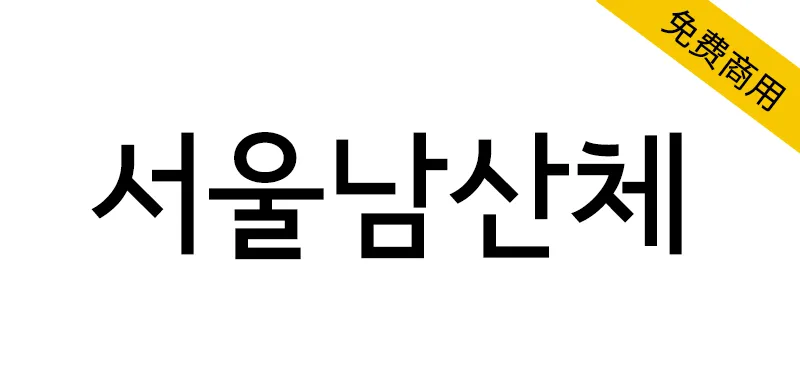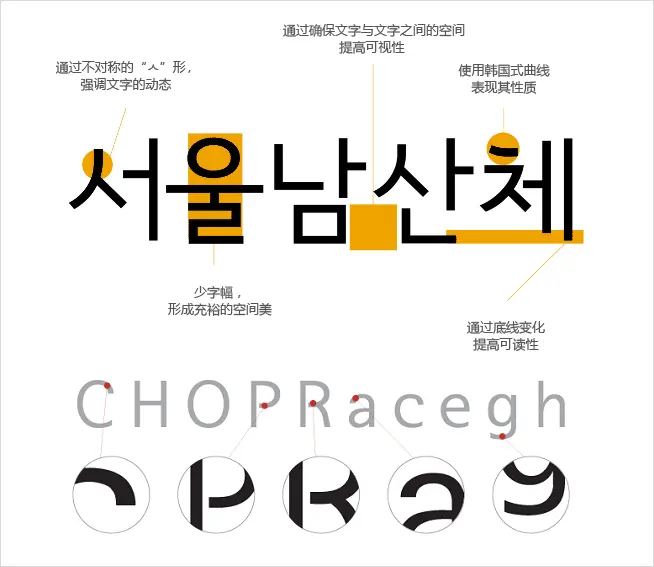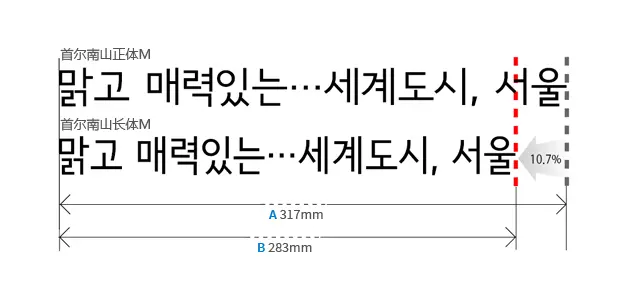
為提升城市認同性與品牌價值而開發出為普及首爾的固有字體,提升城市認同性與品牌價值,韓國首爾市開發出了哥特體系列的4種首爾南山體(Light、Medium、Bold、Extra Bold)。
首爾字體中蘊含著剛正的儒士精神和淡雅的留白之美,從造型上展現了韓屋的開放和瓦片的曲線美。此外,首爾字體取名時採用首爾兩大代表性資源之一的“南山”,更能激發市民對韓民族固有美麗語言——韓文的文化自豪感。
首爾市將首爾字體作為首爾的固有字體而推廣使用,首爾字體可提高城市認同性和品牌價值,開發了
首爾南山體4種(Light、Medium、Bold、Extra Bold)、豎寫1種
首爾南山長體5種(Light、Medium、Bold、Extra Bold、black)。
首爾字體蘊含著正直的儒生精神和端莊典雅的含義,在造形上體現出韓屋的開放性和屋瓦的曲線美。
此外,字體名稱運用了首爾代表性資源之一的“南山”,首爾字體將提高韓民族固美麗語言——韓文的文化自豪感。
通過不對稱的“ㅅ”形,強調文字的動感
減少字幅,形成充裕的空間美
通過確保文字與文字之間的空間提高可視性
使用韓國式曲線表現其性質
通過底線變化提高可讀性